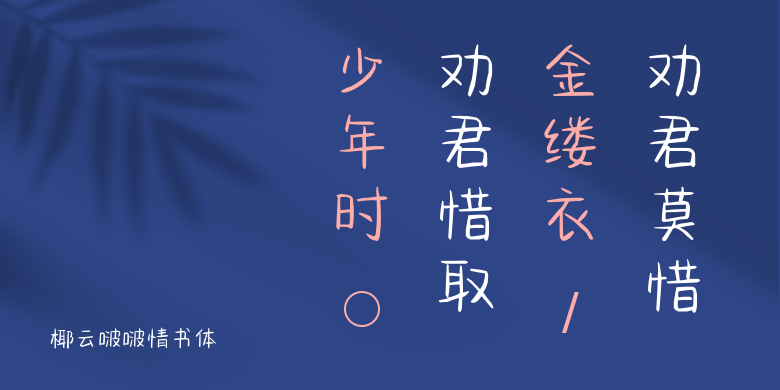
椰云啵啵情书体
椰云啵啵情书体,这款字体结构工整、笔画清晰,兼顾美观与易读性,适用于标题、正文、海报、包装、LOGO 等多种场景。字形优雅稳定,风格百搭耐看,适配日常排版与创意设计,让文字呈现更舒适、更具质感。椰云啵啵情书体一笔一画,皆是细节,以均衡的比例、流畅的线条打造舒适视觉体验,字形端正大气,风格简约现代。无论是商业设计、品牌宣传还是日常排版,都能轻松驾驭,让文字更有格调与力量。椰云啵啵情书体字体下载。